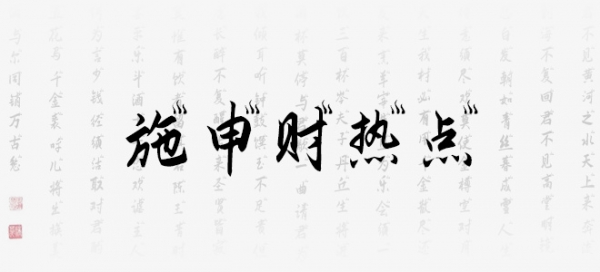
施申財(cái)熱點(diǎn)是一款自帶熱點(diǎn)圖標(biāo)效果的書法藝術(shù)字體,字體筆畫隨性,結(jié)構(gòu)灑脫自在,具有很好的視覺感,適合于文化類的宣傳設(shè)計(jì)、商業(yè)類品牌的廣告和產(chǎn)品包裝設(shè)計(jì)以及個(gè)性化文字排版等較多場(chǎng)景。
施申財(cái)熱點(diǎn)